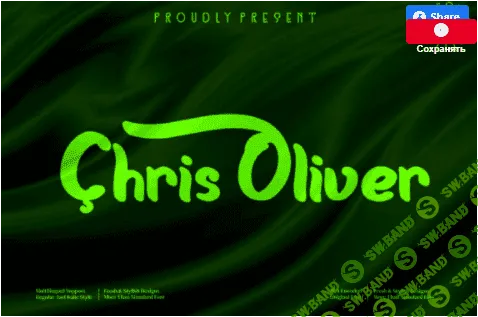
Название: Chris Oliver Font (2022)
Chris Oliver — прекрасный дисплейный шрифт, подходящий для любых проектов, таких как логотипы, брендинговые проекты, дизайн товаров для дома, упаковка продуктов, кружки, цитаты, плакаты, сумки для покупок, футболки, обложки книг, именные карточки, пригласительные билеты, поздравительные открытки, этикетки, фотографии, водяные знаки, специальные мероприятия и все другие ваши роскошные проекты, которым нужен первоклассный вкус.